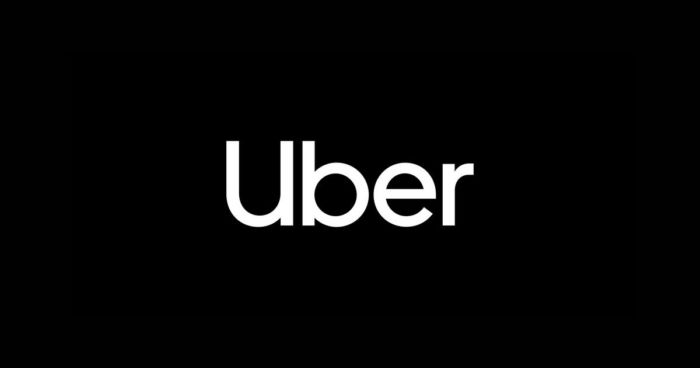
Hace apenas un par de años Uber presentaba su nueva imagen ejecutiva a la sociedad; sin embargo, las marcas siempre deben estar en constante cambio pero sin arriesgar su afinidad con sus consumidores.
Es por ello, que Uber ha decidido renovar su imagen con un nuevo logotipo y una nueva tipografía de la mano de la agencia Wolff Olins; la cual, ha creado una tipografía completamente personalizado que configure con la imagen de amabilidad y accesibilidad que la marca busca inspirar.
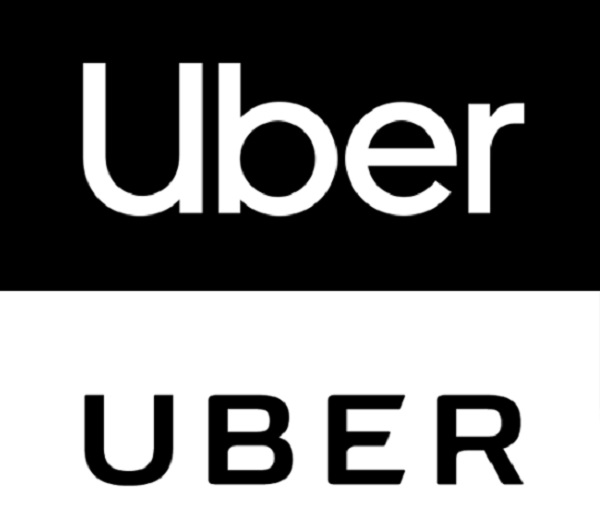
Este nuevo re-diseño pone especial atención en la “U” mayúscula del nombre de la marca; la cual, es muy representativa y brida especial elegancia a la misma.
En fin, de nombre “Uber Move” esta tipografía ha sido inspirada en clásicos como ‘Highway Gothic’ y ‘DIN’; ya que, según señala la agencia tienen una “peculiaridad funcional”, y ademas, es muy legible.
Para terminar, esta nueva imagen y tipografía viene con un re-diseño de la aplicación de Uber; mismo que brinda más fluidez elegancia a todos los usuarios alrededor del globo acorde al estilo ejecutivo.